Bundestagspräsident Lammert präsentierte heute Vormittag den neuen Internetauftritt des Deutschen Bundestages. Im Mittelpunkt des Angebots www.bundestag.de stehen jetzt bewegte Bilder. Debatten und Ausschusssitzungen mit Hintergrundinformationen werden live übertragen. Das Parlament möchte sich in Zukunft den Bürgerinnen und Bürger übersichtlich und täglich aktuell präsentieren.
Die letzte Überarbeitung fand vor 5 Jahren statt. Ein Grund für die »Investition von rund 300.000 €« war die Anpassung des Webauftritts an das neue Corporate Design des Bundestages: neue Wort-Bild-Marke, überarbeiteter Adler, reduzierte Farbgebung (überwiegend schwarz-weiß-grau), Signalfarbe Orange, die Schrift Melior bzw. Georgia für html-Texte. Der Relaunch-Auftrag ging nach einer sechsmonatigen Ausschreibung im Frühjahr an die Düsseldorfer Agentur Babiel, die den Web-Auftritt des Bundestages bereits seit 2004 betreut.
Die Navigation wurde komplett renoviert. Die Datenbanken des Bundestages sind für das Fachpublikum nun besser erreichbar. Informationen für Besucher, Presse, Kunst- und Geschichtsinteressierte sind in Rubriken für Zielgruppen schnell abrufbar. Die aktuellen Online-Petitionen sind direkt auf der Startseite sichtbar. Von dort aus können Bürger online öffentliche Petitionen mitzeichnen oder sie in Foren diskutieren.
Die neue Internetseite erklärt die vielschichtigen Arbeitsebenen des Parlaments und erläutert diese mit Grafiken, Bildern und Beispielen. Wie sieht die Sitzungswoche eines Volksvertreters aus? Wie viel Geld steht ihm für sein Mandat zu? Welche Auskunftspflichten hat er? Die Onlineredaktion wird noch in der Wahlnacht vom 27. September alle biografischen Angaben der neuen Mitglieder des Bundestages in der 17. Wahlperiode aktualisieren.
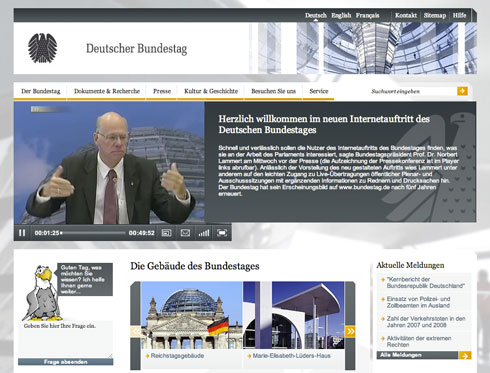
Ich weiss nicht… weiß, grau, orange erinnert mich irgendwie an die CDU-Website.
Sehr gut gelungen.
Und die Melior fand ich schon immer geil.
Was hat denn diese Website mit dem neuen Erscheinungsbild zu tun? außer dem neuen Adler und “Schriftzug” … schluchz, gerade alles neu und schon fangen sie an zu verwässern …
Schick. Das war mal echt nötig!
Durften wieder Testpersonen über das hübscheste Adler-Maskottchen abstimmen? Oder warum erklärt ein amerikanischer Weißkopfseeadler den Bundestag?
Optisch ist der natürlich reizvoll und die braune Farbe der hierzulande lebenden Adler ist im Hinblick auf die deutsche Geschichte nicht gerade ein Glücksfall.
Aber wie wär’s einfach mit schwarz, so wie der Adler im Wappen nun mal dargestellt wird? Einen sorgfältigen Umgang mit Symbolen fände ich schon wünschenswert.
Aber um nicht nur an einem Detail rumzumeckern: Der erste Eindruck von der Seite ist wirklich nicht schlecht.
Die Seite wirkt nun moderner, frischer aber auch etwas unaufgeräumt. Insbesondre beim Scrollen wirkt die rechte Spalte des Content etwas wie MySpace.
Das Adler-Signet gehört zum Corporate Design, den Comic-Adler gab es schon vorher. Siehe Web-Archiv des Deutschen Bundestages z. B. http://webarchiv.bundestag.de/cgi/show.php?id=1082&jahr=2008
Die alte Website war vielleicht nicht besonders stylisch, aber dafür klar und übersichtlich. In diesen Punkten ist die Überarbeitung eher eine Verschlechterung. Besonders das Hintergrundbild wirkt sehr irritierend. Wenn man sich stattdessen zu einem einfarbigen Grund hätte durchringen können und den halben Bundesadler als Wasserzeichen weggelassen hätte wäre schon viel gewonnen.
Das Logo gehört eher auf den Chickengrill von gegenüber. Sieht ein bisschen aus wie eine fette Henne.
Bei einer größeren Auflösung pickt die Seite am linken Rand und das Foto vom Bundestag bricht aus.
Ein bisschen feilen muss man da noch, denke ich.
Gibt es denn irgendwo mehr Informationen bezüglich der Überarbeitung des Corporate Designs. Im Impressum der Seite steht was von büro uebele …
Hübsch. Im Hinblick auf die zukünftige Regierungskoalition ist die Farbwahl sehr visionär. ;-)